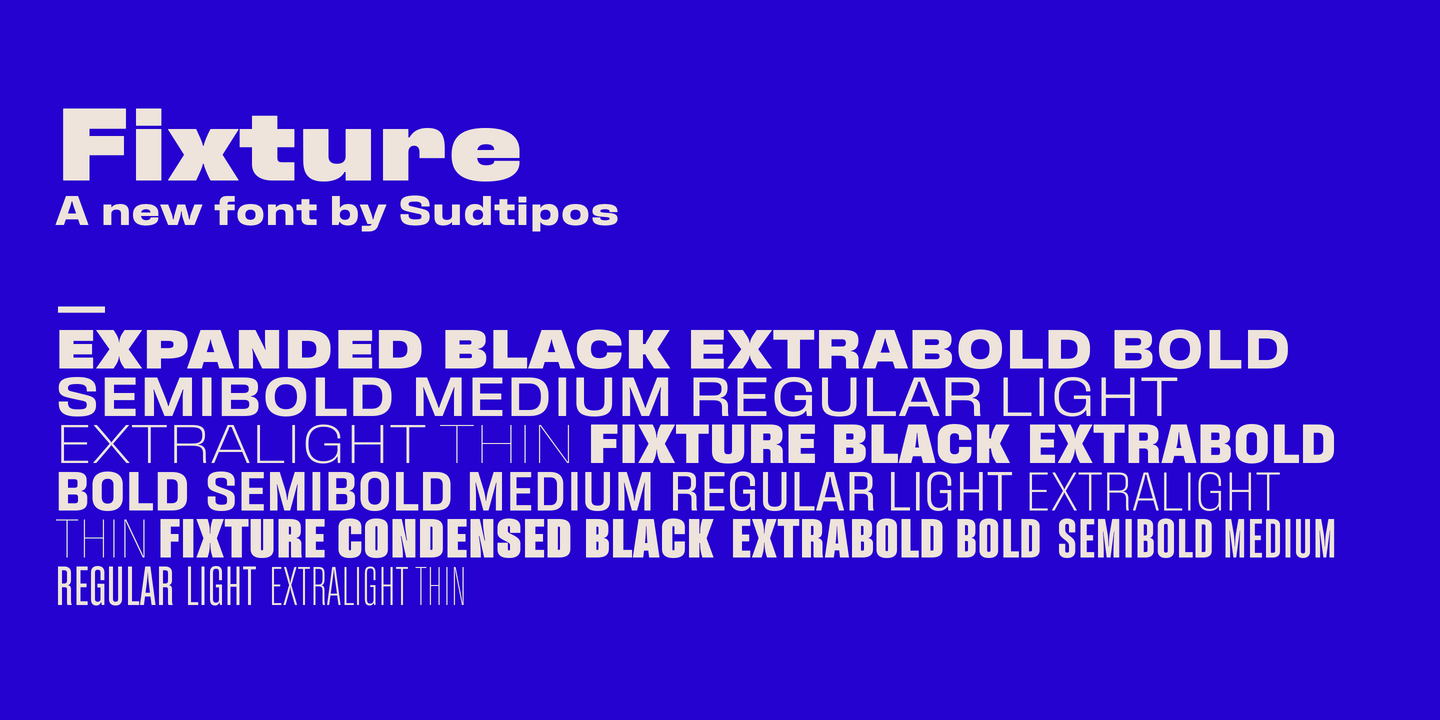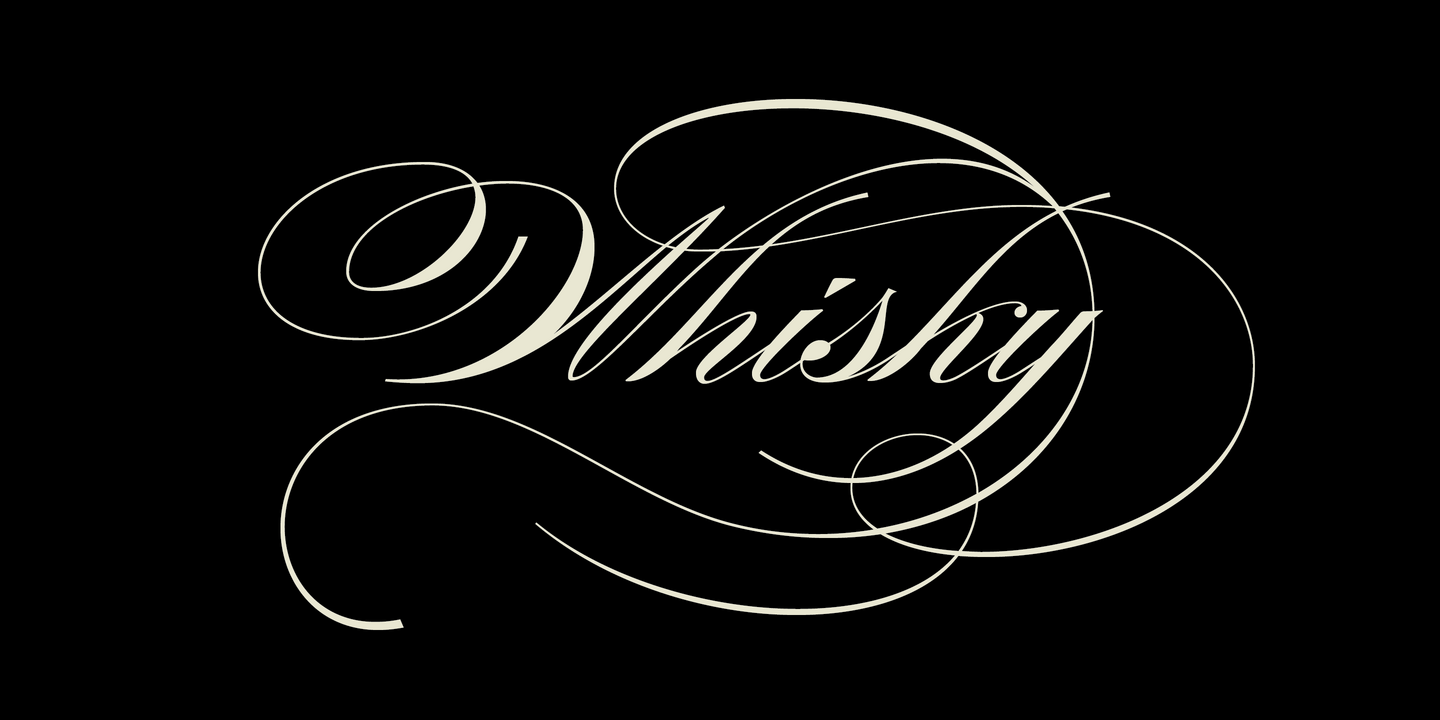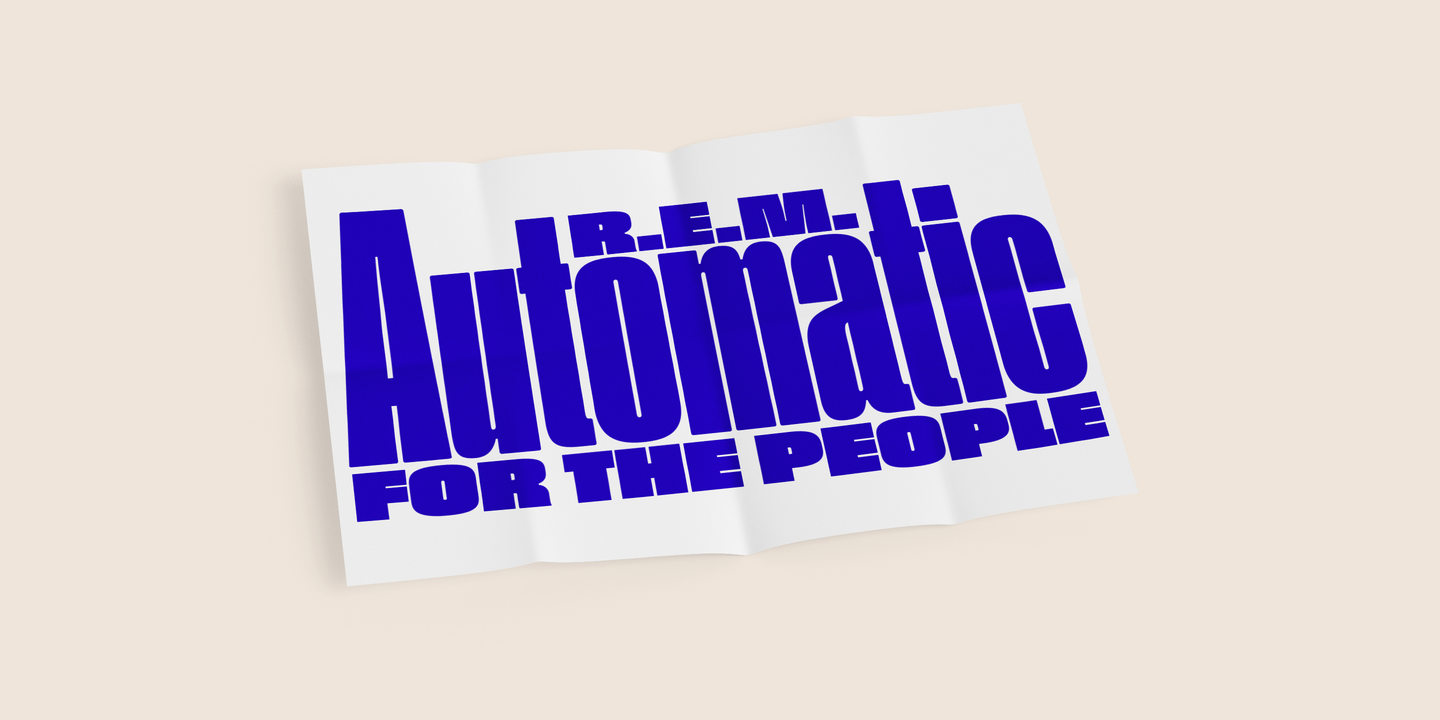
Les créateurs qui composent Sudtipos viennent d'horizons lointains, notamment d'Argentine, de Colombie, d'Espagne, d'Allemagne et du Mexique, pour n'en citer que quelques-uns. La diversité des cultures, des genres et des esthétiques a permis de créer une collection unique de caractères.
Speakeasy est un combo de 5-police construit thématiquement comme un ensemble d'outils pour la conception de menus et d'étiquettes de boissons alcoolisées ainsi que de cafés, de restaurants et d'enseignes lorsque le désir est de communiquer avec style. Conçu à l'origine pour être utilisé par le plus célèbre bar clandestin de Buenos Aires, ce set contient un script, un wedge serif mineur (presque plat), un flare serif, un sans serif, et un bold Didone. La graine du script a été trouvée dans un livre de lettrage allemand, et les autres polices reflètent les styles de publicité et d'annonce familiers du début du 20e siècle.
Fixture est notre version massive de 72-police qui s'inspire d'un grand nombre de caractères, d'affiches et de lettres imprimées sur bois de la fin du 19e siècle, dans le genre Grotesk. Quatre largeurs allant de Ultra Compressed à Expanded sont proposées avec neuf graisses et les italiques correspondantes. Certaines alternatives sans-serif courantes, telles que le a et le g, sont incluses dans tous les polices. L'idée de ce design était de créer une famille de caractères police avec suffisamment de flexibilité fonctionnelle pour fonctionner dans de multiples environnements, de la subtilité de la mise en page d'un magazine ou d'un générique de film au drame visuel des panneaux d'affichage ou de l'emballage.
Burgues Script est une ode au calligraphe américain de la fin du XIXe siècle Louis Madarasz, dont la plume légendaire a inspiré les écoles de calligraphie pendant plus de 100 ans. Son talent a valu à certains de le qualifier de "plus habile styliste que le monde ait jamais connu". J'utilise le mot "ode" dans un sens familier et ambitieux. Si j'étais un vrai poète, mes mots porteraient sur des choses que je désire mais que je ne peux pas atteindre, sur des objets d'une beauté absolue qui me font sombrer dans l'humilité, ou sur des personnes au talent énorme qui me regardent du haut des nuages du génie. Mais je n'écris pas de poèmes. Mon travail consiste en des lettres dessinées pour s'emboîter, qui deviennent un élément de la poésie visuelle de quelqu'un.
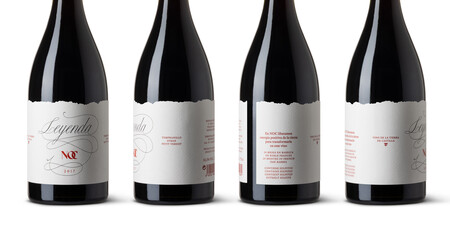
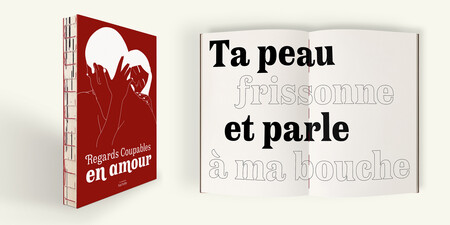
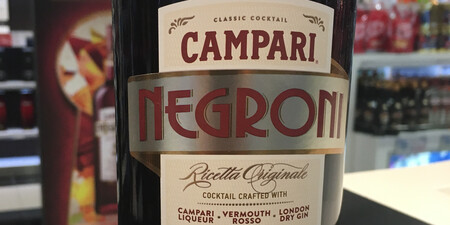
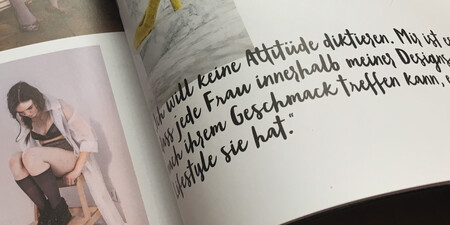
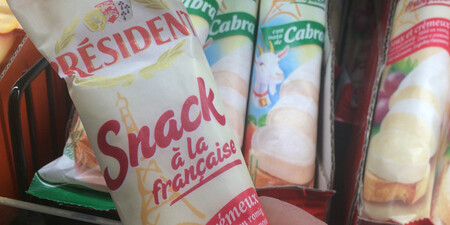
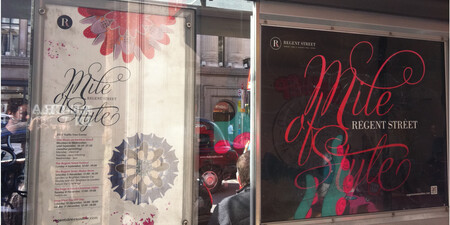
À la recherche constante de nouvelles niches typographiques à explorer et s'efforçant toujours de suivre les avancées technologiques, Sudtipos est présent sur le marché depuis 20 ans et s'est imposé comme l'une des fonderies de caractères les plus récompensées et les plus utilisées dans le monde du design. Ses projets vont de la typographie exquise pour l'emballage à des systèmes typographiques complexes pour le texte. Les caractères Sudtipos n'ont pas de frontières puisque ses créateurs sont répartis dans le monde entier.
Alejandro Paul
Ale Paul est l'un des fondateurs du projet Sudtipos et une référence clé pour la qualité de son travail. Son travail a énormément contribué à placer l'Argentine sur la carte du graphisme. La carrière d'Ale en tant que directeur artistique l'a amené à travailler dans certains des studios les plus prestigieux d'Argentine et à s'occuper de marques d'entreprises aussi prestigieuses que Procter & Gamble, SC Johnson, Danone et d'autres. Avec la fondation de Sudtipos, Ale a réorienté ses efforts vers la conception de caractères, créant polices, des lettres et des caractères commerciaux pour plusieurs agences d'emballage de premier plan. En 2012, son police a été sélectionné pour Letter2. Il a reçu quatre certificats d'excellence du Type Directors Club NY et plusieurs prix à la biennale de typographie Tipos Latinos.
Il enseigne un programme de typographie de troisième cycle à l'université de Buenos Aires, où il a précédemment enseigné la conception graphique. Il a également donné des séminaires et des conférences lors des Type Master Weeks NY, TypoBerlin, TypeCon, Pecha Kucha et Atypi, au Type Directors Club de New York et lors d'événements à Hong Kong, en France, en République tchèque, en Autriche, en Espagne, au Portugal, au Chili, au Brésil, en Colombie, en Équateur, au Venezuela, en Bolivie, en Uruguay, au Mexique et au Canada. Son travail a été présenté dans des publications du monde entier, notamment Eye, Communication Arts Print, Creative Review, Visual, Creative Arts, Novum et bien d'autres. Il a été désigné délégué national d'ATypi et est membre de l'Alliance Graphique Internationale - la première pour l'Argentine.